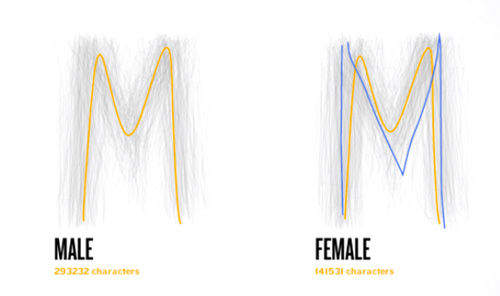
Hasta ahora The Universal Typeface promedia los más de medio millón de caracteres escritos a mano y enviados por personas desde un centenar de países. El experimento es del fabricante de boligrafos Bic —de los Bic naranja escribe fino, Bic cristal escribe normal de toda la vida.
A partir de los trazos recibidos (cualquiera puede enviar el suyo) se genera un trazo promedio que es lo que Bic llama la Tipografía Universal. Al parecer han recibido trazos desde todos los rincones del Universo.
Un aspecto curioso del experimento es que permite cotillear cómo son los trazos y trazos promedio resultantes filtrando por país, género, edad, sexo; y por zurdos y diestros.